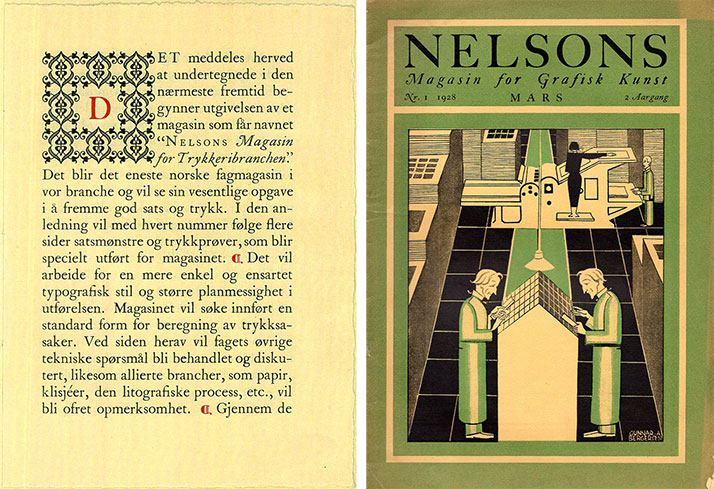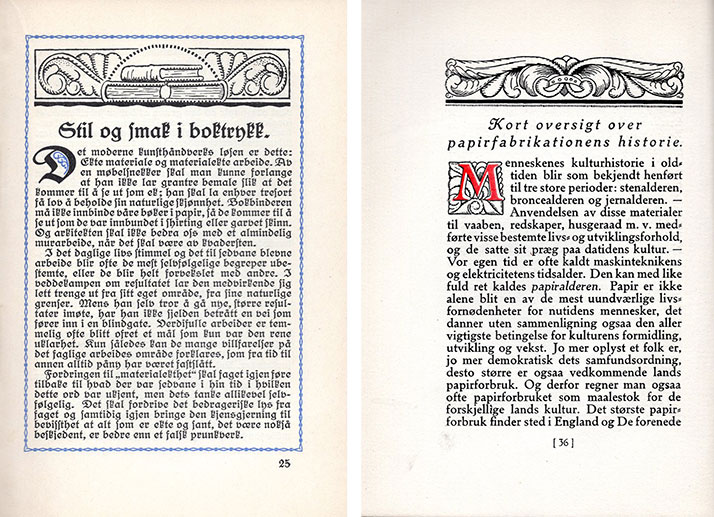
Arthur Nelson er en av de mest interessante boktrykkerne i norsk grafisk historie. Hans faglige virke fra slutten av 1800-tallet fram til annen verdenskrig var svært allsidig. Gjennom sitt tidsskrift Norsk Trykk ble han en viktig person i det grafiske fagmiljøet.
Arthur Nelson gikk veien fra den såkalte «frie retning» på slutten av 1800-tallet til amerikansk klassisk typografi på begynnelsen av 1900-tallet. Tilbake i Norge arbeidet han for en klassisk retning i norsk typografi – i motsetning til en nasjonal stil, som mange ønsket. Deretter formidlet han prinsippene for den funksjonalistiske «nye typografien» i sitt eget fagtidsskrift.
Disse stilhistoriske brytningene er interessante. Norsk boktrykkhistorie har mange hull, men Arthur Nelson representerer et stort hull, som denne artikkelen skal prøve å fylle.
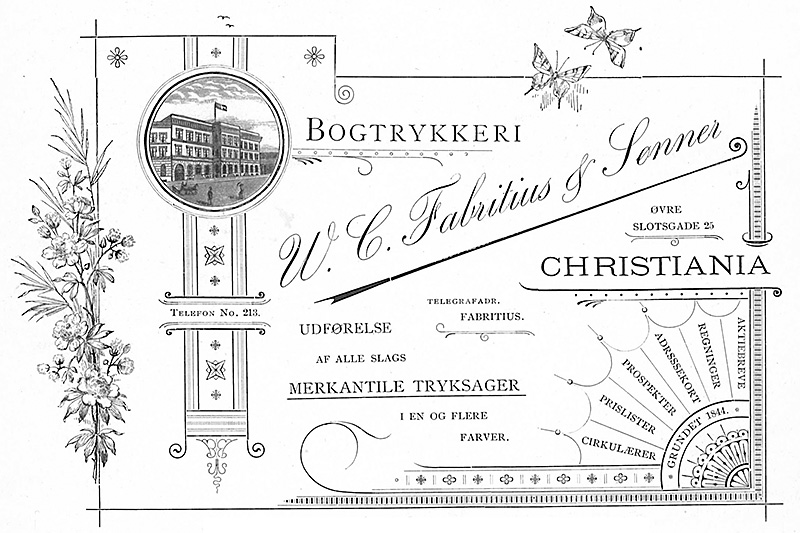
Et eksempel på «den frie retning», som var den rådende stilretning da Nelson gikk inn i boktrykkfaget. Fra Hermann Scheiblers Lære- og mønsterbog for typografer, Christiania 1896. Scheibler var faktor (arbeidsleder) i Fabritius boktrykkeri, der Arthur Nelson var læregutt mens Scheibler skrev på sin bok.
Den frie retning
Da Arthur Nelson startet sin læretid i 1893, var nivået på norsk boktrykk lavt. Men som læregutt i W. C. Fabritius & Sønner i Kristiania kom han under vingene på en ypperlig fagmann – Hermann Scheibler.
På denne tida var «den frie retning» den herskende typografiske stil i Norge, som i mange andre land. Arthur Nelson beskrev seinere den frie retning slik: «Der fremstilles trykksaker som fråtser i dekorasjoner. Der kommer på markedet skrifter av alle mulige fasonger i følge med forsiringer som varierer i det uendelige.» Han kalte perioden «smakløshetens tid».
Da Arthur Nelson var ferdig utlært i 1897, hadde han det beste faglige fundament man kunne få i Norge. Mange år etter skrev han: «Jeg blev utlært efter alle teknikens regler under en tysk faktor og tysk akcidens-sætter; jeg var naadd saa langt i teknik at jeg som syttenaars læregut deltok i den første skandinaviske annoncekonkurranse og vandt 5te præmie paa et fuldstændig aandløst produkt; men teknikken var der.»
Norske trykkerier kjøpte på denne tida i stor grad tysk skriftmateriell og tyske maskiner, og var derfor under sterk innflytelse av tysk typografi. Det var også et markert innslag av tyske fagfolk i norske trykkerier.
Årene i USA
Etter noen år som aksidenssetter, faktor og bestyrer i forskjellige trykkerier i Kristiania og Trondheim, reiste Arthur Nelson til USA i 1902.
Han fikk et godt inntrykk av forholdene i den grafiske bransjen i USA: de amerikanske trykkeriene var «en fornøielse for en Fagmand at færdes i». Og videre: «Alt hvad vi hjemme anser for det eneste rigtige er herover fulstændig det modsatte. De har insett at de er minst ligesaa kloge som sine tyske kolleger og de har mange Penge.»
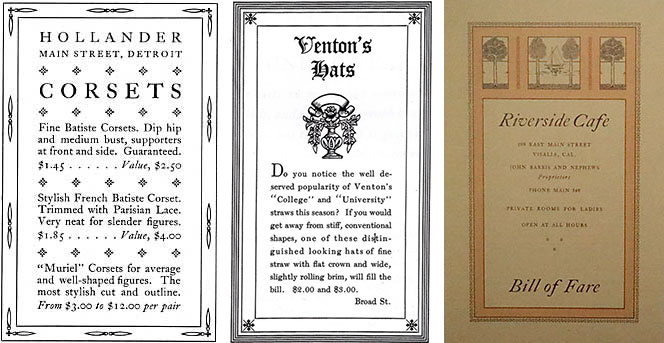
Til venstre to eksempler på amerikansk klassisk orientert typografi, fra American Type Founders’ fagtidsskrift The American Chap-Book, mai 1905. Nelson brakte denne utgaven med tilbake til Norge. Til høyre en meny, satt med Caslon, signert Arthur Nelson i USA. Den ble avbildet i Type Designs in Color, utgitt av Oswald Printing Co. (1912), der Nelson var ansatt. Den ble så vist i Graham Hudsons faghistoriske utgivelse The Design & Printing of Ephemera (2008). En flott anerkjennelse av Nelsons amerikanske karriere!
Arthur Nelson reiste tilbake til Norge i 1904. Men etter et år som aksidenssetter i Kristiania reiste han til USA på ny i 1906. Han nådde denne gang langt: blant annet var han ansatt i The Oswald Press i New York, som utga fagbladet The American Printer. Seinere skrev han om disse årene: «Efter et aar som akcidenssætter blev jeg bestyrer av trykkeriet og tillike ‘uttegner’ av satsprøvene i The American School of Typography, en serie satsmønstre der hver maaned medfulgte The A. P. som bilag. Disse 7 aar var de mest frugtbringende av mit liv, idet jeg fik frie hænder til hver maaned at skape nye satsideer. Den forbindelse som bladet hadde med faget over hele verden gav mig da ogsaa anledning til at følge med tiden.»
Arthur Nelson ble premiert i flere satskonkurranser arrangert av nordamerikanske fagtidsskrifter. Ansettelsen i The Oswald Press var for øvrig en følge av at han vant tredje premie i en konkurranse arrangert av The American Printer. Han arbeidet også i reklamebransjen.
De strømningene i amerikansk typografi som Nelson ble kjent med i USA, var vesensforskjellige fra læretida i Fabritius. Den klassiske typografien – altså de historiske antikvaskrifter, symmetriske, harmoniske oppsett, forsiktige virkemidler – hadde en renessanse. Som i Storbritannia, ble Caslon-typene igjen tatt i bruk.
Nelson skrev noen år etter: «Den typografi som vore vestlige kollegaer idag anvender, er intet andet end smaken fra vort haandverks bedste tid, som de med sin tillempningsevne har utviklet til fuldkommenhet og tilpasset amerikanske forhold. Mens vi endnu holdt paa med fraktur og snirklede bokstaver, begyndte de at bruke de gamle mesteres skrifter, som Jenson, Caslon, Bodoni etc.»
Tilbake til Norge
Arthur Nelson returnerte til Norge for godt i 1920. I bagasjen hadde han flere reoler med amerikanske Caslon-typer, med tanke på å starte eget trykkeri.
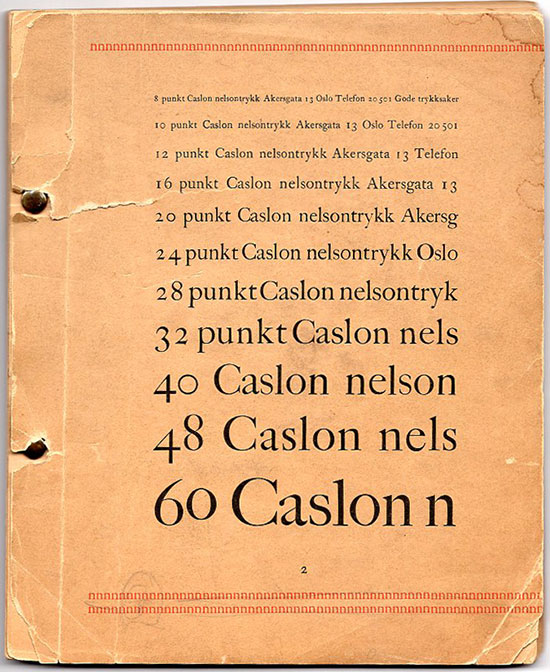
Arthur Nelson (1878–1957), født Nielsen. Bildet er trolig fra omkring 1920, året da han returnerte til Norge fra USA.